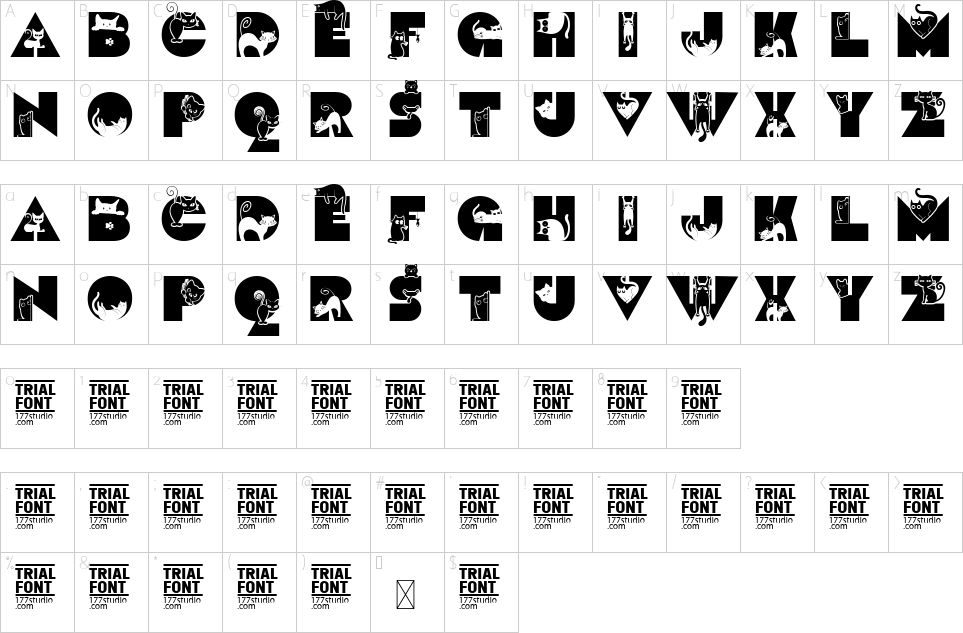
Descubra a beleza e a simplicidade da fonte Apache Tomcat, ideal para projetos de software e desenvolvimento web. Inspirada no popular servidor Apache Tomcat, esta fonte é perfeita para aplicativos Java e outras soluções de servidor web. Desenvolvida pelo estúdio 177studio.com, a fonte Apache Tomcat não só ajuda a personalizar seu ambiente de trabalho, mas também transmite uma identidade visual que valoriza tecnologia e inovação. Oferecida gratuitamente para Windows e Mac, a fonte Apache Tomcat é uma escolha inteligente para qualquer projeto que deseje uma aparência sólida e elegante. Com uma baixa frequência de download de 1.192 vezes, essa fonte se destaca entre os muitos recursos disponíveis para designers.